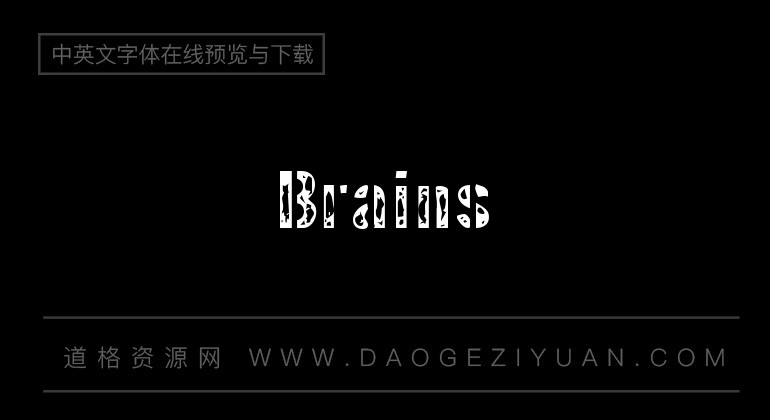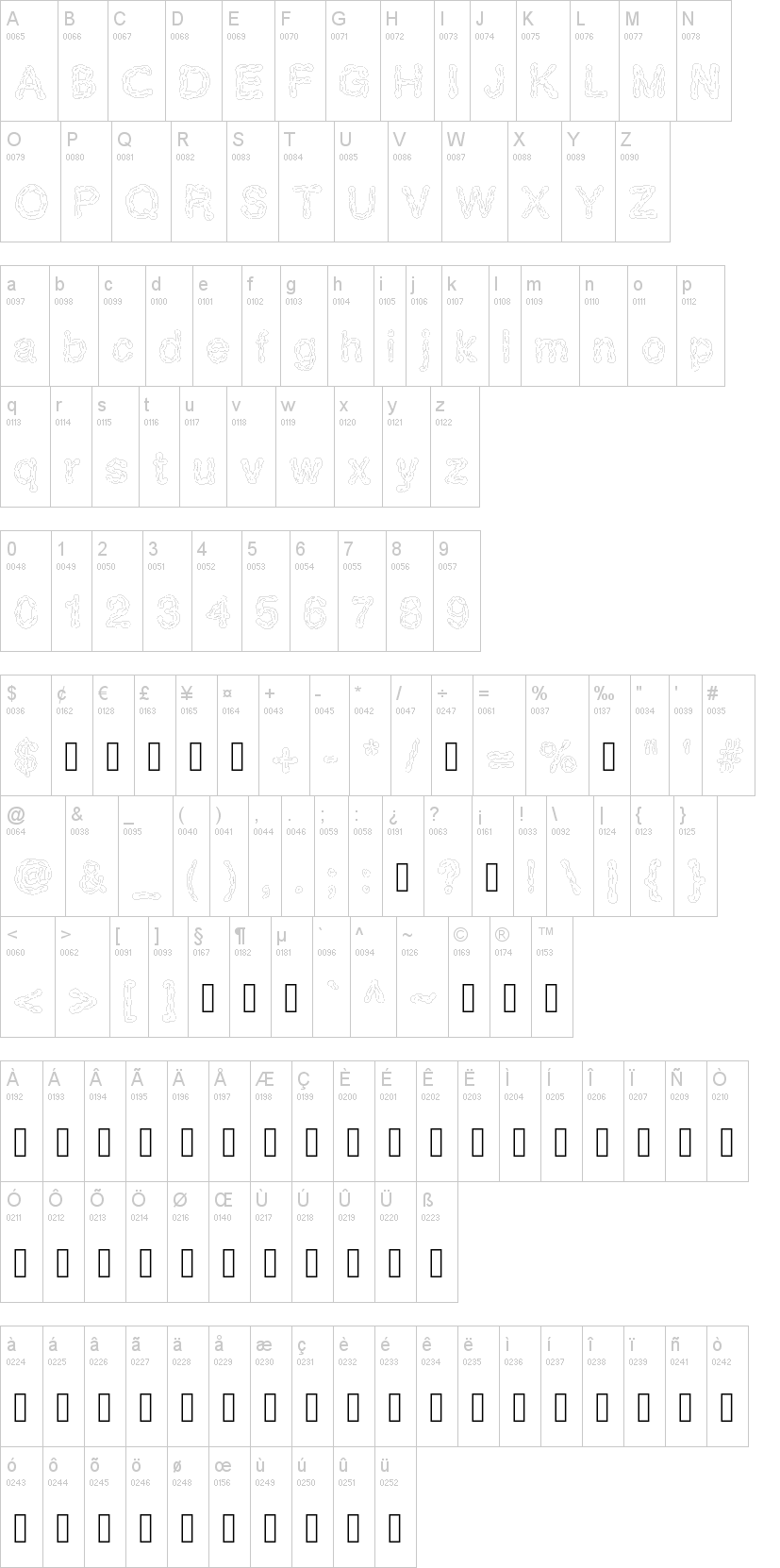
Brains 字体是一种不规则的手写风格字体,具有非常独特的个性和视觉吸引力。它的字母形状不完全对称,有时会出现笔画交叉或字母的一部分会延伸到其他字母的下方。这种不规则的设计使得它在许多设计场合中非常受欢迎,例如印刷品、广告、海报、包装、书籍封面等。 与其他手写字体不同的是,Brains 字体设计师刻意在字母之间添加了一定的空间,以增强阅读体验和可读性。因此,即使在小字体的情况下,它也能保持清晰易读。此外,该字体还提供了一些有趣的替代字母和装饰符号,可以进一步增强设计的创意和个性化。 Brains 字体提供多种字重和风格,从细到粗,从常规到斜体等,可以满足不同设计需求。它是一款非常适合用于突出个性和创意的字体,同时也适用于许多其他设计场合。内容介绍
Brains是一款非常不错的手写艺术字体,具有很好的视觉感,适合于文化类的宣传设计、商业类品牌的广告和产品包装设计以及个性化文字排版等较多场景。